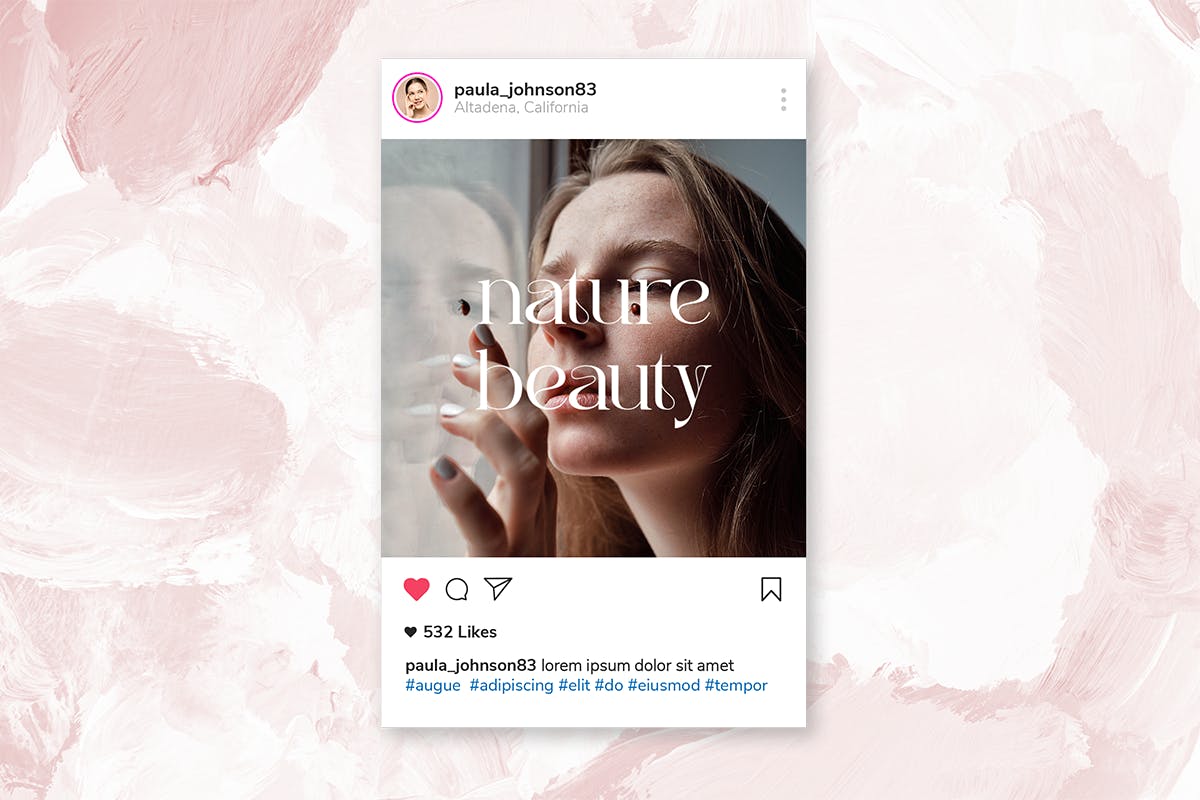
Kegger یک نوع فونت نمایشی شیک است که حروف بزرگ و برجستهای با جزئیات تزیینی منحصر به فرد در هر کاراکتر را ارائه میدهد.
این فونت حس کلاسیک و جذابی را به همراه دارد و در عین حال بهروز و مطابق با روندهای طراحی فعلی به نظر میرسد.
Kegger برای پروژههای مختلفی که نیاز به ظاهری لوکس و چشمنواز دارند، مناسب است. این پروژهها میتوانند شامل دعوتنامههای عروسی، طراحی بستهبندی محصولات لوکس یا مواد تبلیغاتی برای برندهایی باشند که به دنبال انتقال تصویری خاص و مجلل هستند. این فونت سریف همچنین برای طراحی لوگو یا طراحی وبسایت که هدف آن نمایش ظاهری خلاقانه و شیک است، مناسب میباشد و در عین حال ظاهری حرفهای و کلاسیک را حفظ میکند.